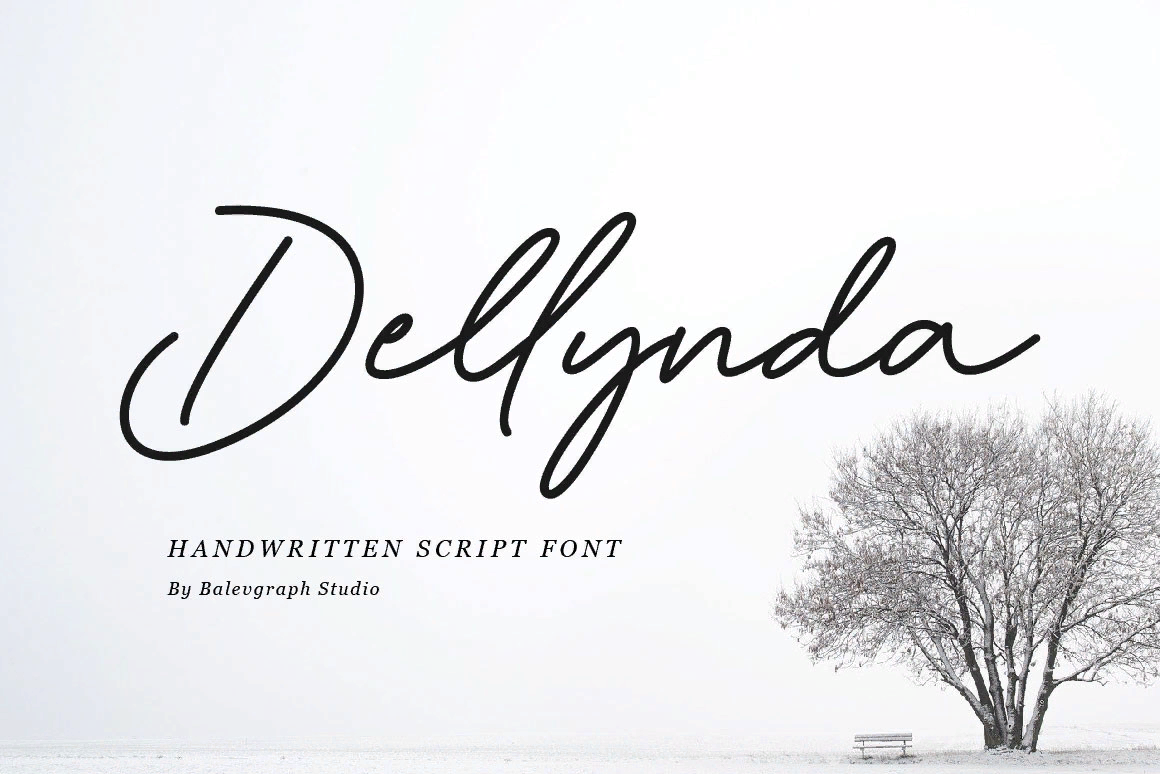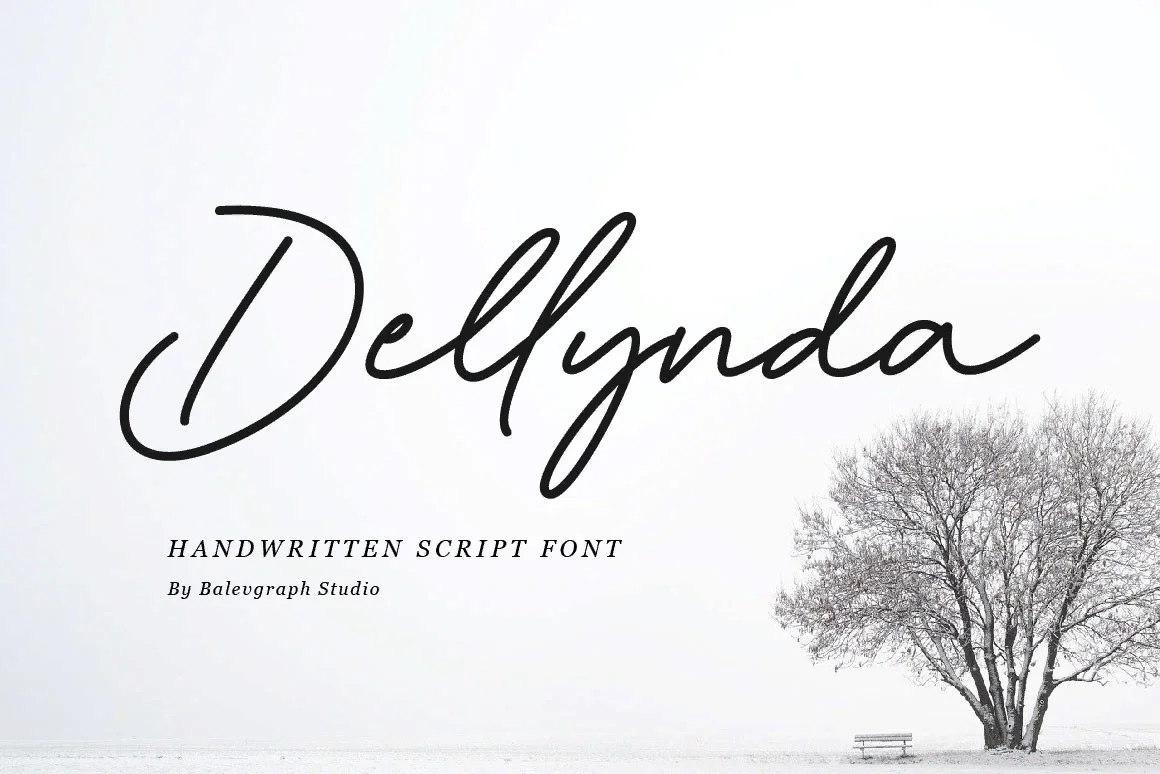
Название: Dellynda Font (2021)
Dellynda - это модный шрифт с тонким начертанием.
Влюбитесь в его восхитительный стиль и используйте его для создания великолепных свадебных приглашений, красивых канцелярских принадлежностей, привлекательных постов в социальных сетях и многого другого!